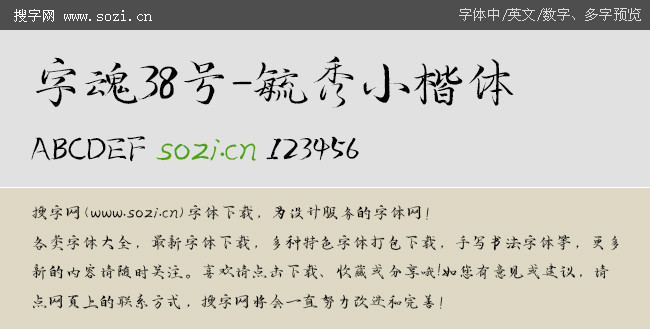
字魂38號-毓秀小楷體
搜字網(wǎng)提供一款字魂38號-毓秀小楷體中文字體下載,該字體是一款硬筆手寫字體,該字體包含6989個中文、字母、 符號和數(shù)字,具有浪漫、溫柔、古典、婉約、手寫風(fēng) 的風(fēng)格,可以滿足您設(shè)計上的各種需求,該字體主要用于廣告、影視傳媒、新媒體、電商、健康養(yǎng)生 等場景。